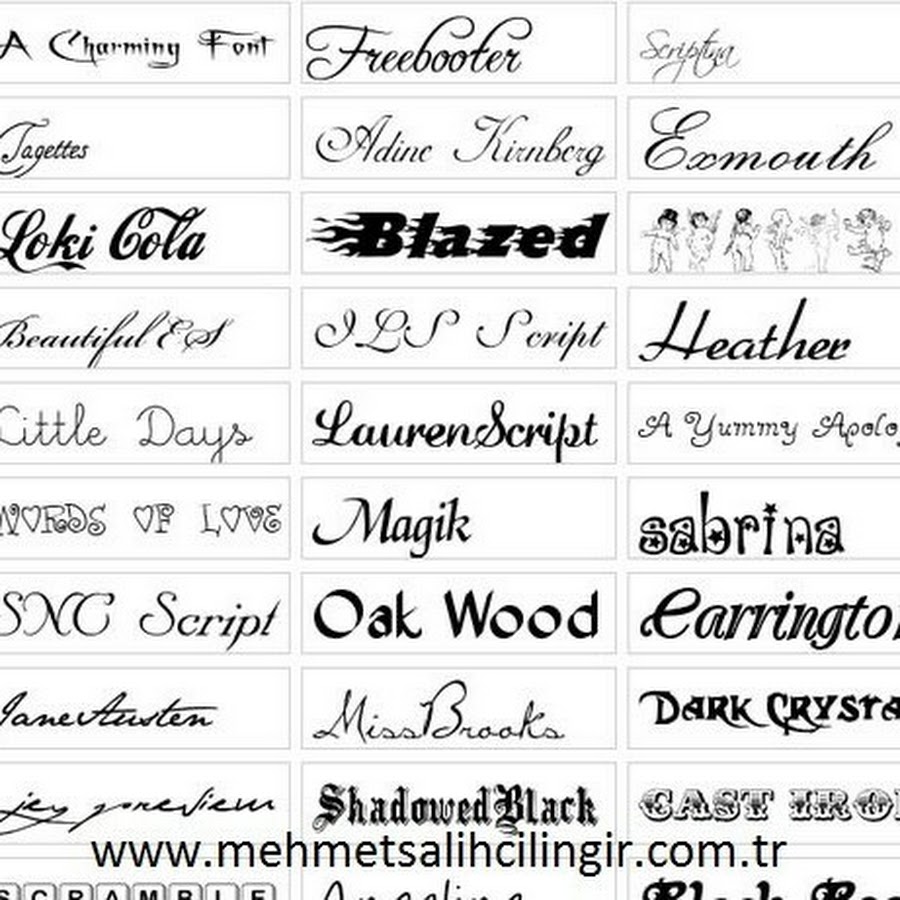
Красивые шрифты для фотошопа бесплатно: Скачать бесплатно шрифты для Фотошопа
Красивые бесплатные декоративные шрифты для фотошопа
Свежая подборка красивых бесплатных декоративных шрифтов для фотошопа.
Почему именно для фотошопа? Все просто — эти шрифты чисто декоративные. Из них не имеет смысла набирать длинные тесты.
Декоративные шрифты можно с успехом использовать в отрисовке всевозможных флаеров, свадебных приглашений, для плакатов, афиш, вывесок, тату, баннеров и в веб-дизайне, разумеется, тоже.
Все шрифты созданы профессиональными дизайнерами, поэтому о качестве можно не волноваться. Также на все шрифты распространяется бесплатная лицензия, по которой вы можете использовать их как для частных, так и для коммерческих проектов, за исключением продажи самих шрифтов. Большая часть представленных шрифтов выполнена в рукописном стиле.
1. Setta Script — красивый и элегантный современный рукописный шрифт
Красивый и стильный шрифт Setta Script. Этот шрифт отлично подойдет для оформления свадебных приглашений, либо его можно использовать, как шрифт для тату, или как шрифт для меню в кафе или ресторане.
2. Frutilla Script — очень красивый и выразительный рукописный шрифт
Красивый и выразительный рукописный шрифт Frutilla Script идеально подойдет для брендирования, а также для оформления любых поздравительных открыток, рисунков, дизайна и пр.
Очень трогательный, привлекательный, располагающий и проникновенный шрифт.
3. Breakable — смелый и решительный рукописный шрифт
Шрифт Breakable прекрасно подойдет для оформления торговой марки, логотипа, любых поздравительных открыток, стильного оформления рисунка или любого дизайна, который нуждается в естественном и личном контакте. Этот шрифт несколько грубоват, но решителен и смел, стилизован под «сухую кисть».
4. Rainwood — бесплатный наивный рукописный шрифт в стиле кисти
Бесплатный и несколько наивный рукописный шрифт Rainwood словно бы нарисован неровной рукой школьника с помощью толстой кисточки. Однако это лишь на первый взгляд. На самом деле каждая буква этого шрифта тщательно продумана и выверена. Этот шрифт отлично подойдет для оформления меню в кафе или небольшом ресторанчике, а также для различных открыток, флаеров, концертных плакатов и т.п.
5. Rachella Script — современный красивый каллиграфический шрифт для фотошопа
Шрифт Rachella Script чем-то похож на Frutilla Script, но с большим количеством завитушек и более округлый. Так же идеально подойдет для создания логотипов, брендирования, оформления всевозможных поздравительных открыток, рисунков, дизайнов и пр. Очень элегантный, привлекательный, располагающий и красивый шрифт.
6. Signatura Monoline — стильный и тонкий рукописный шрифт
Шрифт Signatura Monoline, как следует из его названия, очень похож на подпись. Это так же современный и стильный тонкий рукописный шрифт. Его можно с успехом применять как для оформления различных открыток, так и для графического дизайна в целом.
7. Priscilla Script — современный каллиграфический бесплатный шрифт
Богатый и стильный каллиграфический шрифт Priscilla Script содержит 282 глифа и 109 альтернативных символов.
Этот прекрасный шрифт — сама красота и элегантность! Разумеется, его можно и нужно применять для создания потрясающих дизайнов, привлекательной рекламы, ресторанных меню, и ярких поздравительных открыток.
8. Just Smile — веселый и жизнерадостный рукописный шрифт
Just Smile — просто улыбнись! 🙂 Симпатичный и простой рукописный шрифт Just Smile хорошо подойдет для множества графических и дизайнерских работ. Это и открытки, и вывески, и рекламные плакаты и многое другое. Не содержит лишних украшательств, прост, красив и при этом несколько игрив. Улыбайтесь, господа! 🙂
9. Quickline Script — тонкий и элегантный бесплатный рукописный шрифт
Тонкий и элегантный рукописный шрифт Quickline Script отлично подойдет для оформления свадебных приглашений, а также для различных постеров, флаеров, ресторанных меню, логотипов и пр.
10. Facunda Font — тонкий и высокий шрифт с тенью для фотошоп
Facunda Font — это тонкий и высокий шрифт с тенью.
Сейчас дизайнеры очень часто используют в своих работах подобные шрифты для оформления логотипов, рекламной продукции, брендирования и даже для заголовков.
Skyfont сделает ваш текст похожим на табло полетной информации в аэропортах. Этот шрифт идеально подходит для создания креативных заголовков и заголовков для веб-сайтов.
Moalang — стильный бесплатный дисплейный шрифт с уникальными художественными изгибами и декоративными элементами. Шрифт можно использовать для создания креативных обложек книг, плакатов, листовок и т. Д.